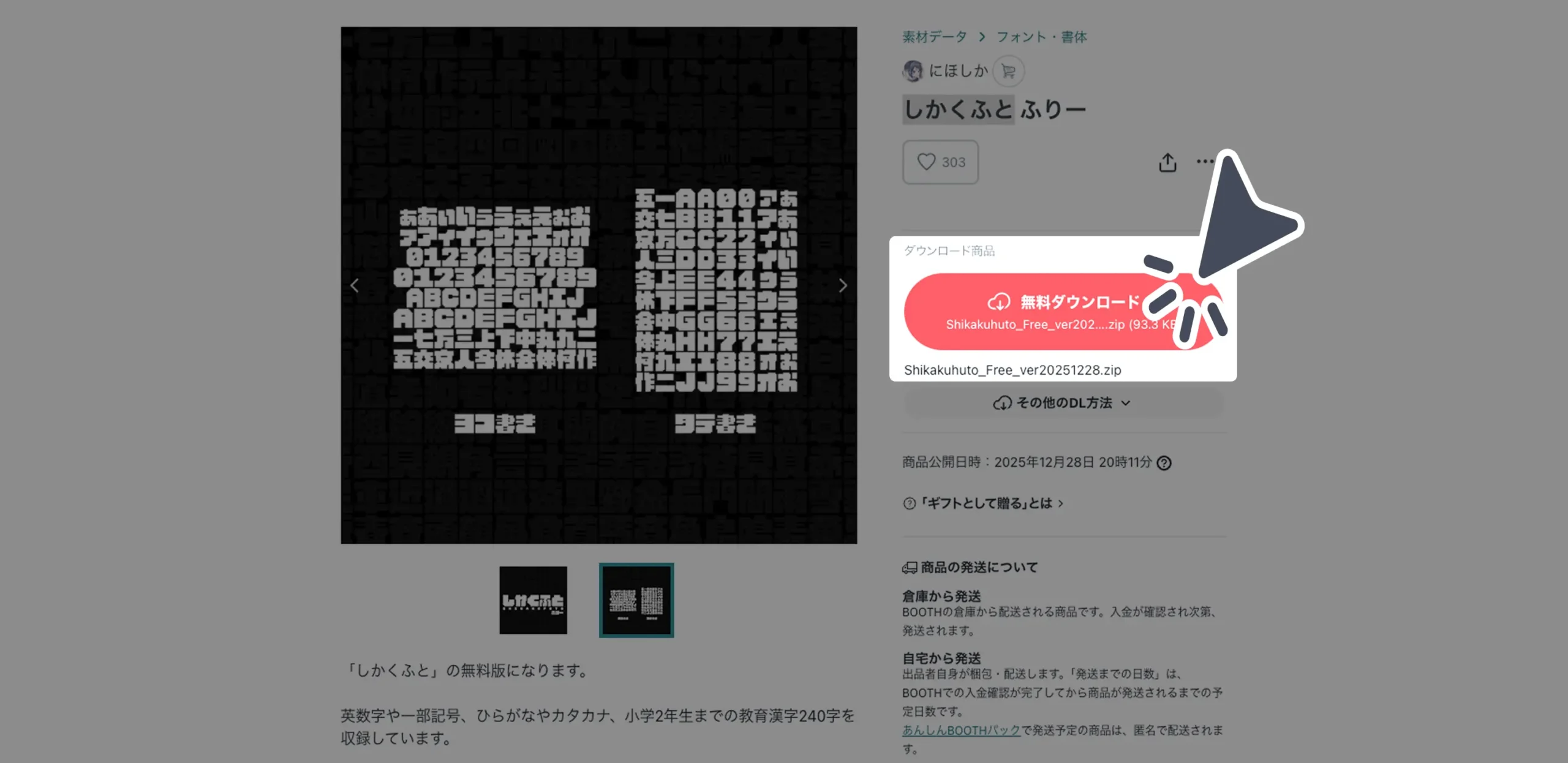
四角く太い線で構成された、見た瞬間に強さが伝わるデザインフォントです。一文字一文字の主張がはっきりしており、短い言葉でもしっかり目に留まります。ロゴやタイトル、アイキャッチなど、視線を集めたい場面に向いており、ゲーム系やイベント告知とも相性が良いのが特徴です。文章向きではありませんが、「印象を残す文字」として使うことで、デザイン全体の存在感を高めてくれます。
しかくふと